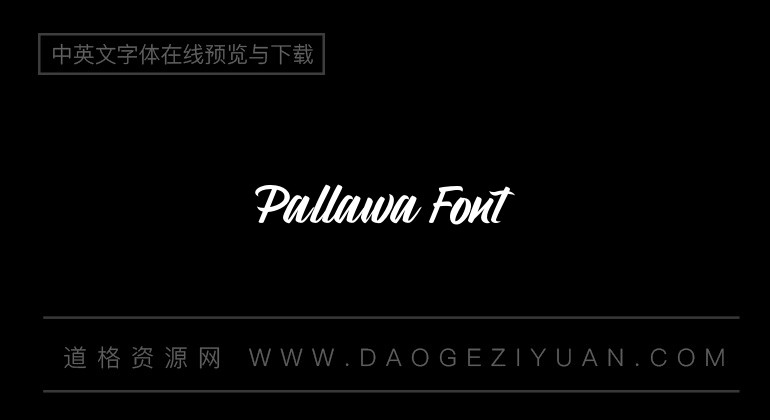
Pallawa Font是一种的装饰性字体,它源自于印度的卡纳达语,也被称为卡那达文。这种字体具有非常独特的外观和特征,它们在卡纳达文中被广泛使用。 Pallawa Font的特点是字母形状极其优美,造型典雅,较为独特,字体线条流畅,具有一定的装饰性和书法美感。Pallawa Font也被广泛应用于卡纳达文印刷材料中,如书籍、报纸、杂志等。 此外,Pallawa Font也是一种免费的字体,任何人都可以下载和使用。有很多网站提供Pallawa Font的下载,非常方便。内容介绍
Pallawa Font是一款非常不错的手写艺术字体,具有很好的视觉感,适合于文化类的宣传设计、商业类品牌的广告和产品包装设计以及个性化文字排版等较多场景。